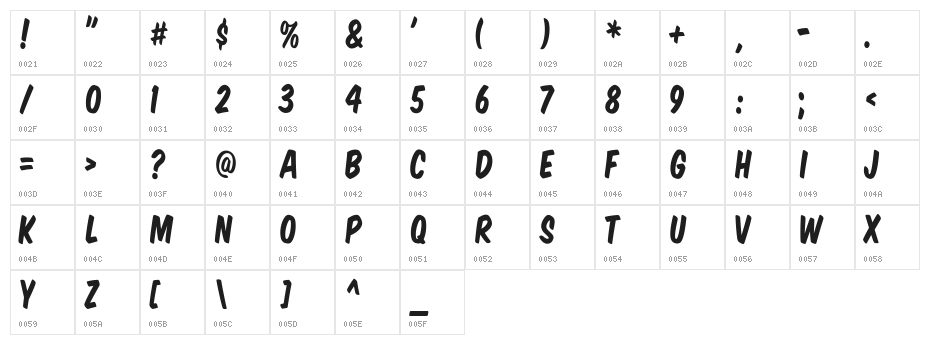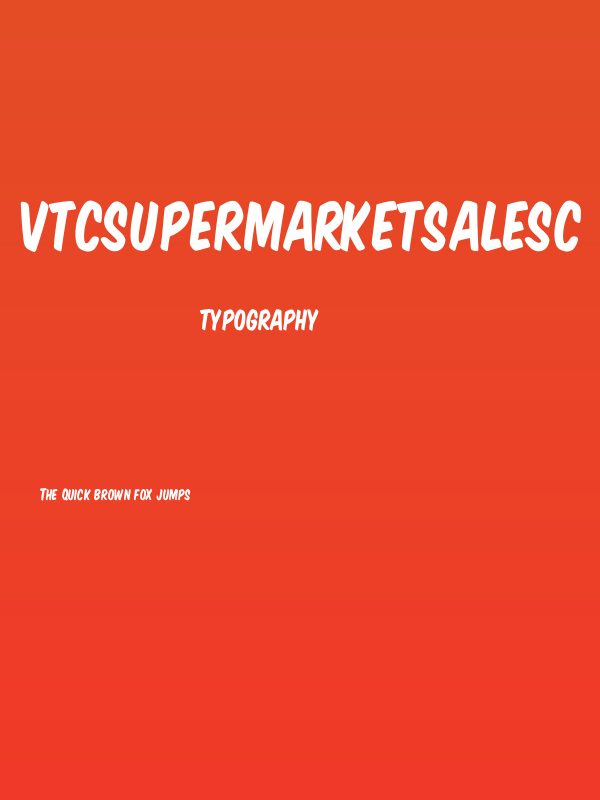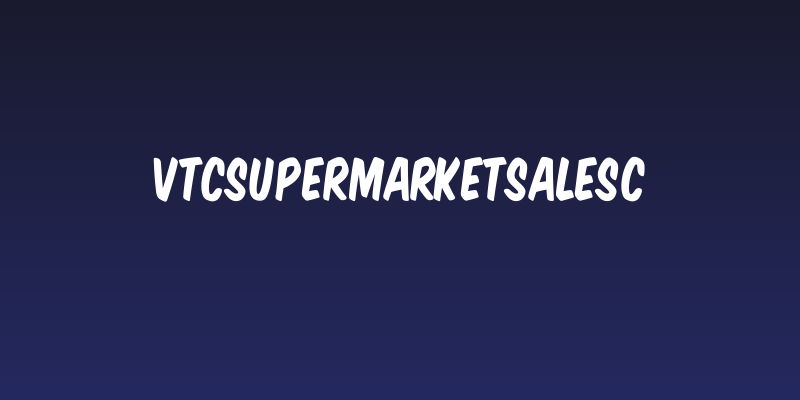
VTCSuperMarketSaleSC Font
| النمط العام | Playful, Energetic |
| حالة الاستخدام | Headlines, Posters, Branding |
| مشاريع مقترحة | Ideal for posters, advertisements, children's books, and branding materials that require a lively and engaging appearance. |